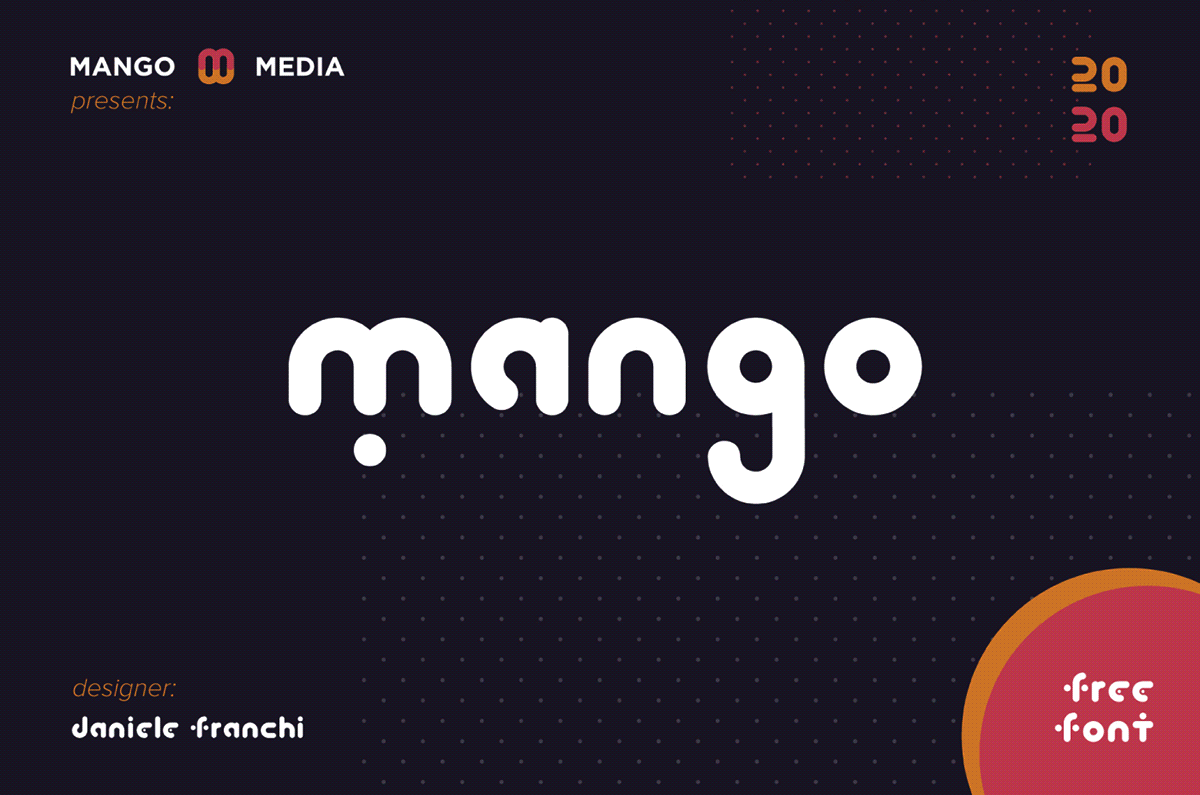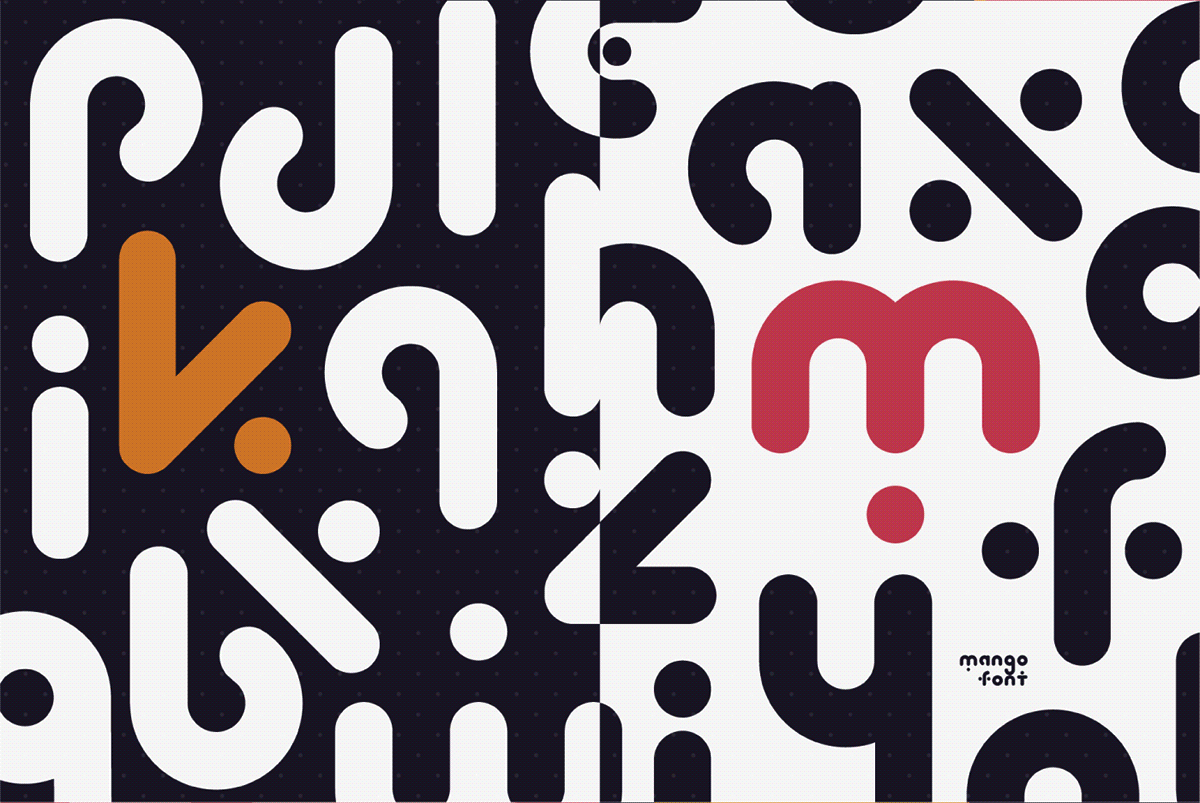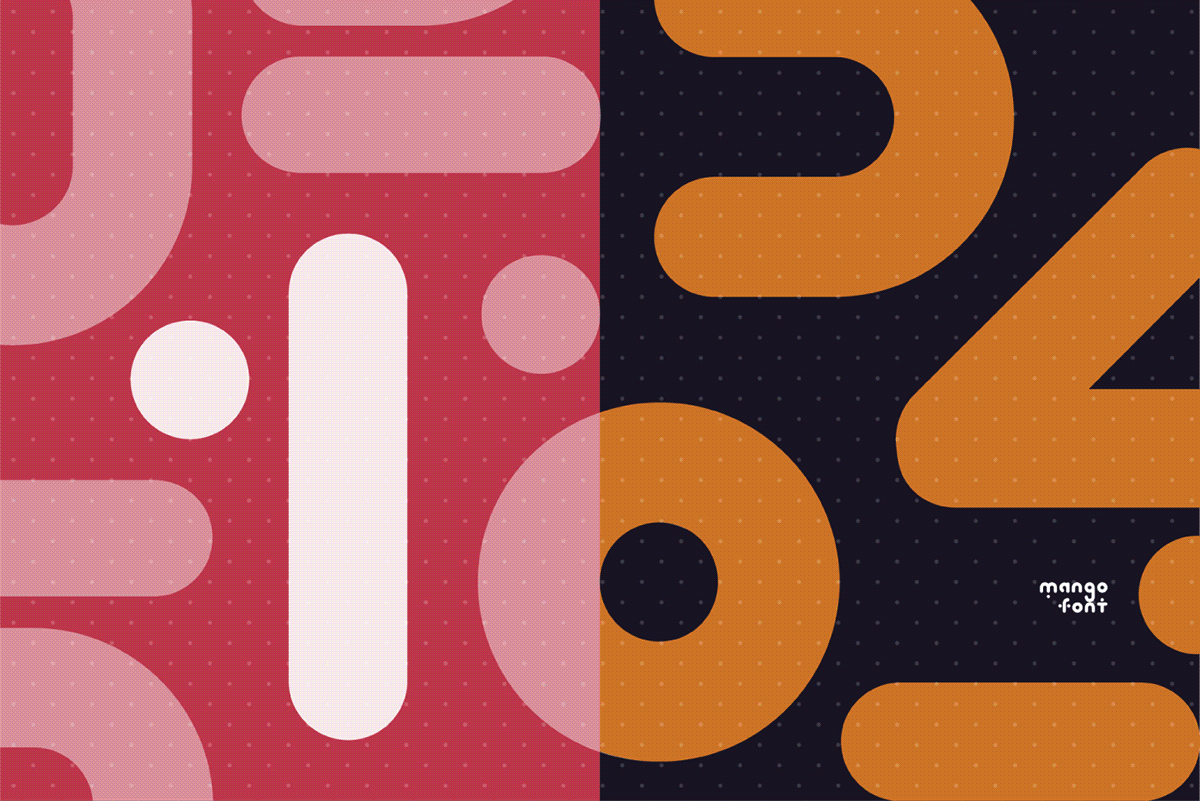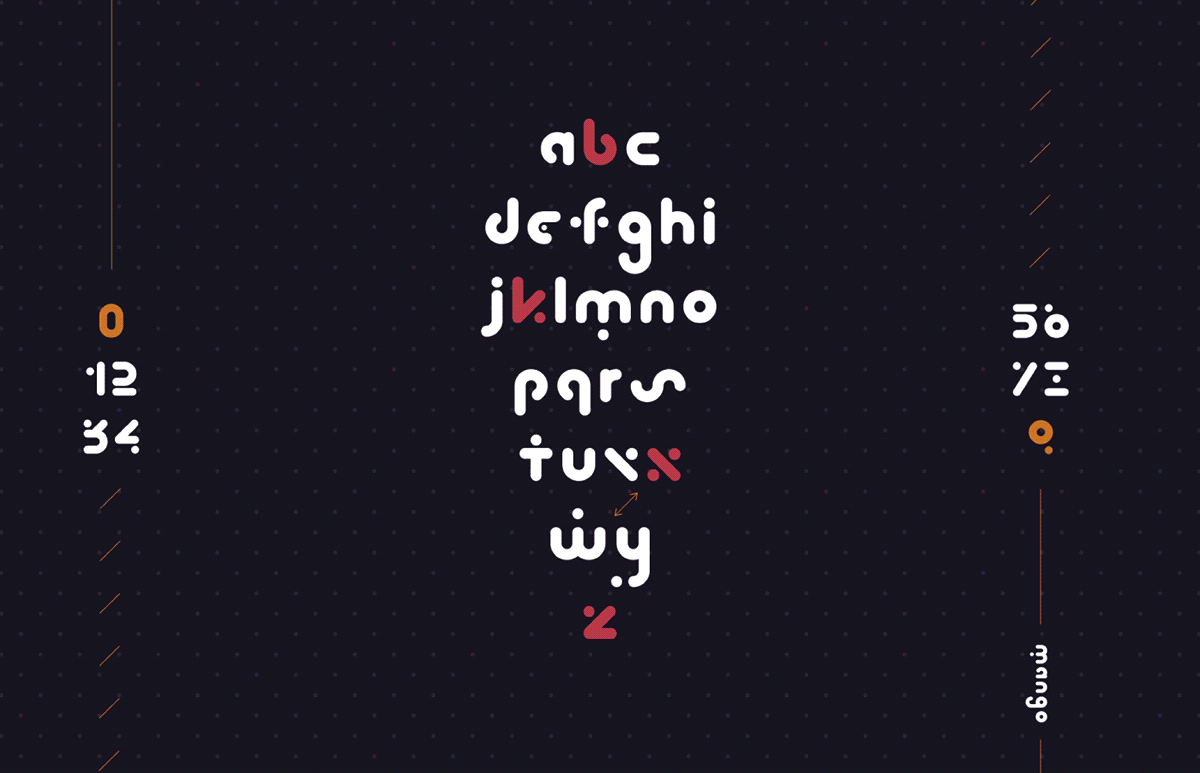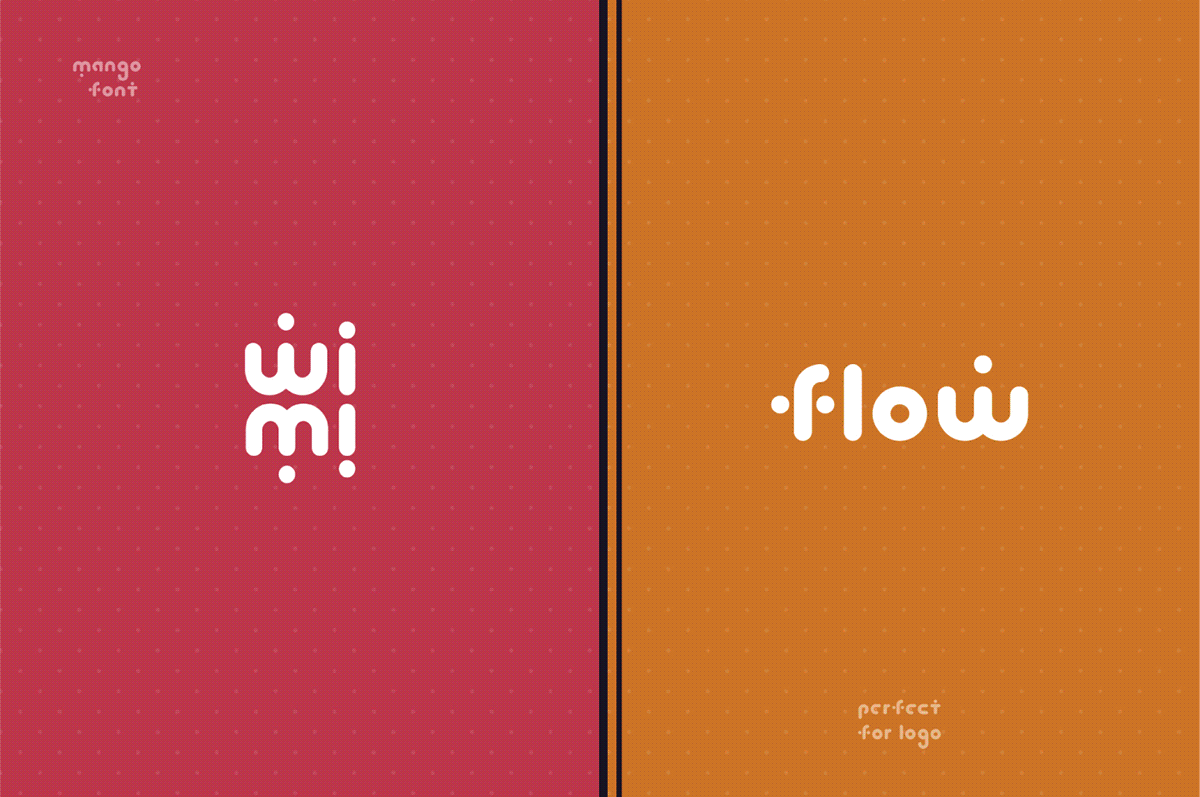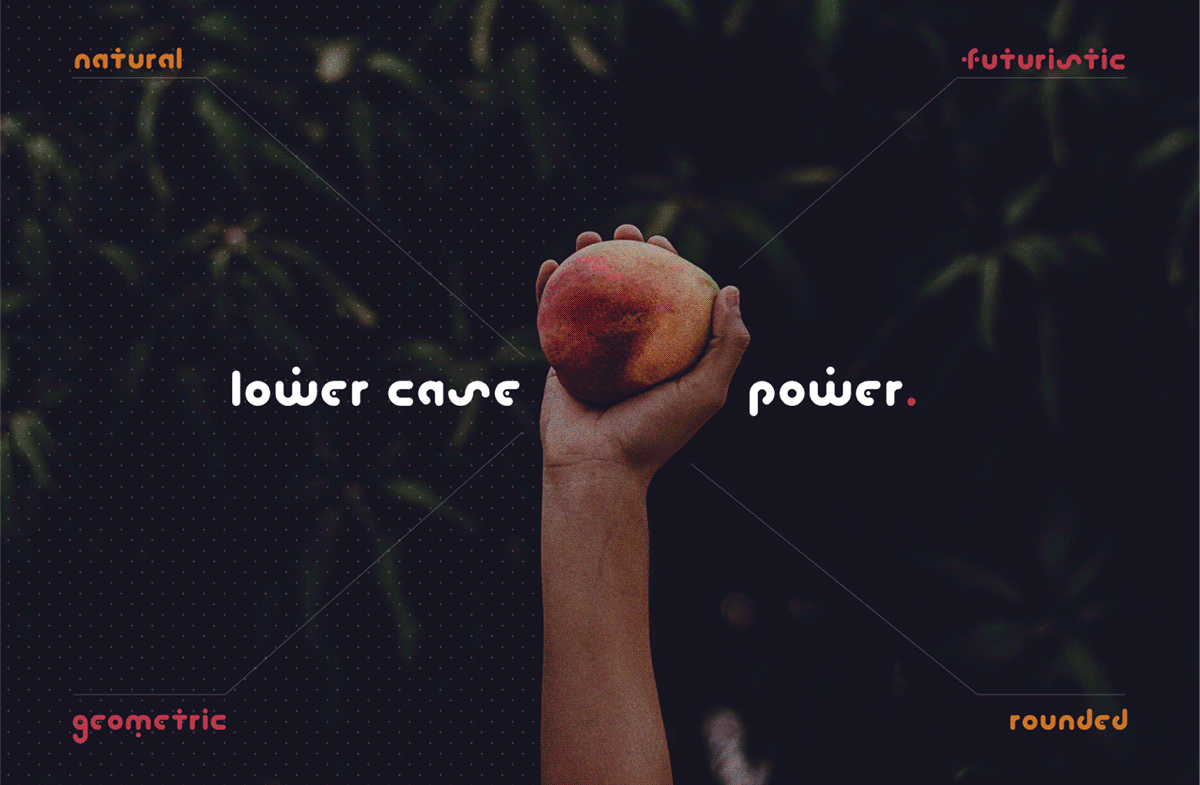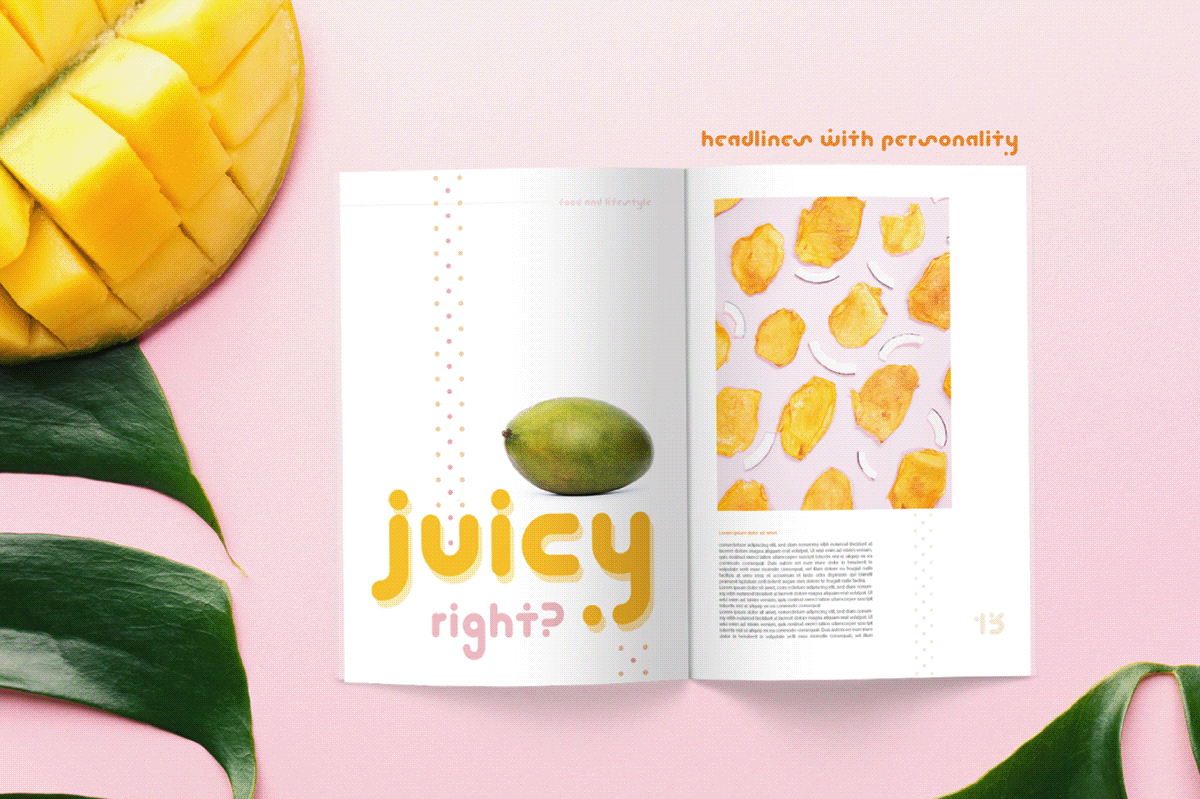
Mango
Mango 是一款免费的几何极简英文字体,由设计师 Janice Franchi 为庆祝加入都柏林创意机构 Mango Media 而创作并发布。字体仅采用小写字母设计,以圆润流畅的几何结构构建字形,将未来感、极简主义与趣味性巧妙融合,呈现出鲜明的品牌辨识度和现代设计气质。
从字形设计来看,Mango 采用大量圆角与几何曲线作为视觉语言,笔画粗细均匀,转角圆润自然,整体造型简洁却富有个性。设计师通过大胆的留白、独特的字母连接关系以及富有节奏感的结构比例,让每个字符既保持较高的识别度,又兼具图形化特征。整体视觉风格轻松活泼,带有浓厚的未来科技感,非常适合打造具有年轻化、数字化特征的视觉形象。
Mango 虽然字符集较为精简,但正因其独特的设计语言,在品牌 Logo、海报标题、包装设计、UI 界面、社交媒体封面、动态图形以及科技、互联网、创意类项目中都拥有出色的表现力。尤其在大字号展示时,字体的几何美感与现代气质能够得到充分展现,为作品带来极高的视觉记忆点。
以下是设计师官方提供的样张,供大家品鉴参考:
Mango 以圆润的几何造型、极简未来主义风格和鲜明的品牌辨识度,成为一款极具个性的免费商用英文字体。它特别适用于 Logo、标题、科技产品、UI 设计及各类创意视觉项目,对于追求现代感、年轻化与设计感的作品来说,是一款兼具视觉冲击力与实用价值的优质字体选择。